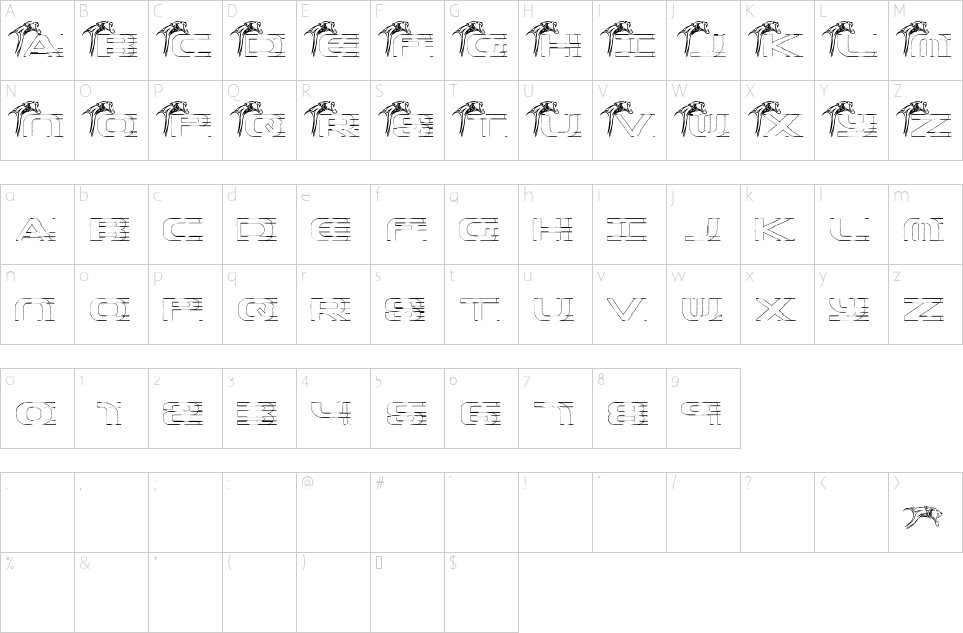
Descubra a elegância da Panther Font, uma opção gratuita para adicionar um toque único ao seu trabalho gráfico. Desenhada por Isaac K, esta fonte é uma excelente escolha para designers buscando uma solução prática e versátil. Com mais de 3.123 downloads, é evidente que muitos profissionais já apreciaram suas sutis nuances e modernidade. Seja para criar logotipos, publicações digitais ou qualquer tipo de material gráfico, a Panther Font pode oferecer a solução perfeita. Não perca tempo, baixe sua cópia da Panther Font hoje e transforme seu design em um verdadeiro show de talento.